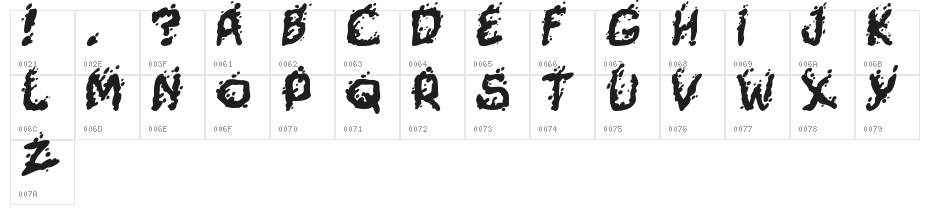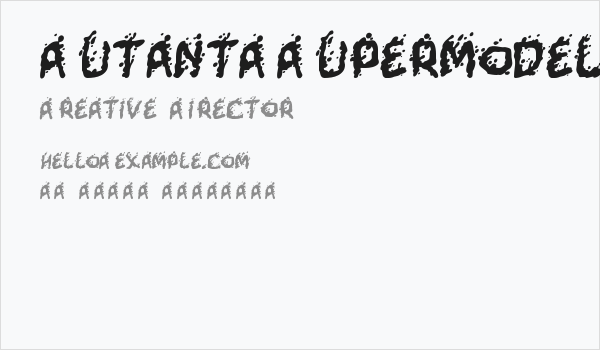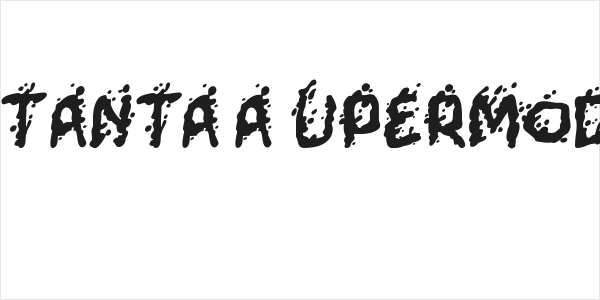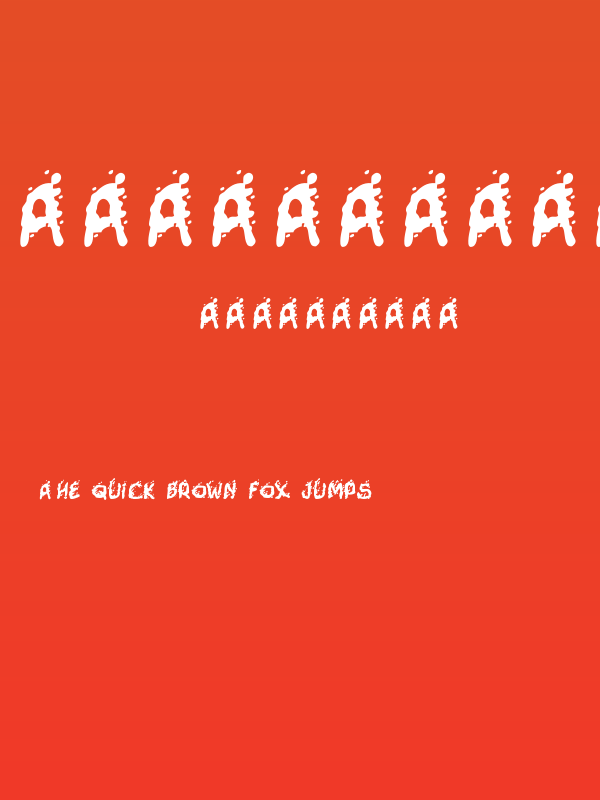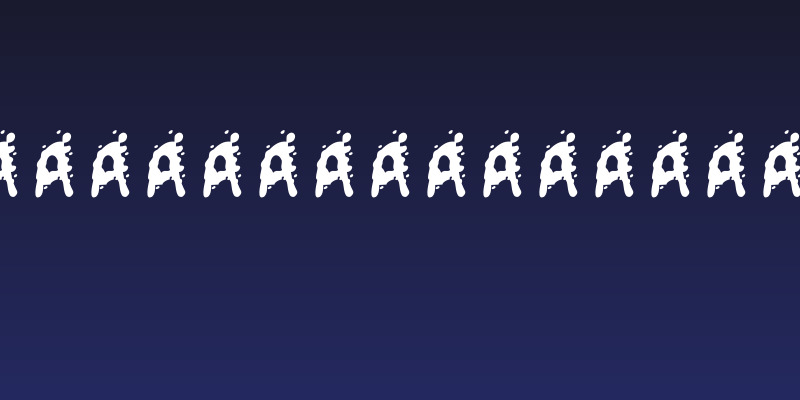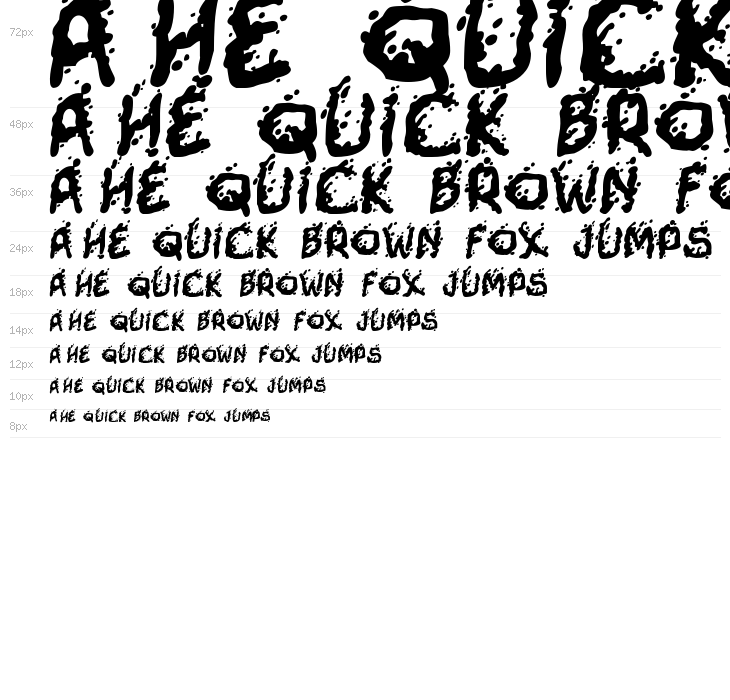
Mutant-Supermodel Font
| Anwendungsfall | Headlines, Posters, Creative Designs |
| Vorgeschlagene Projekte | Ideal for Halloween-themed designs, edgy posters, album covers, or any project requiring a bold, artistic flair. |